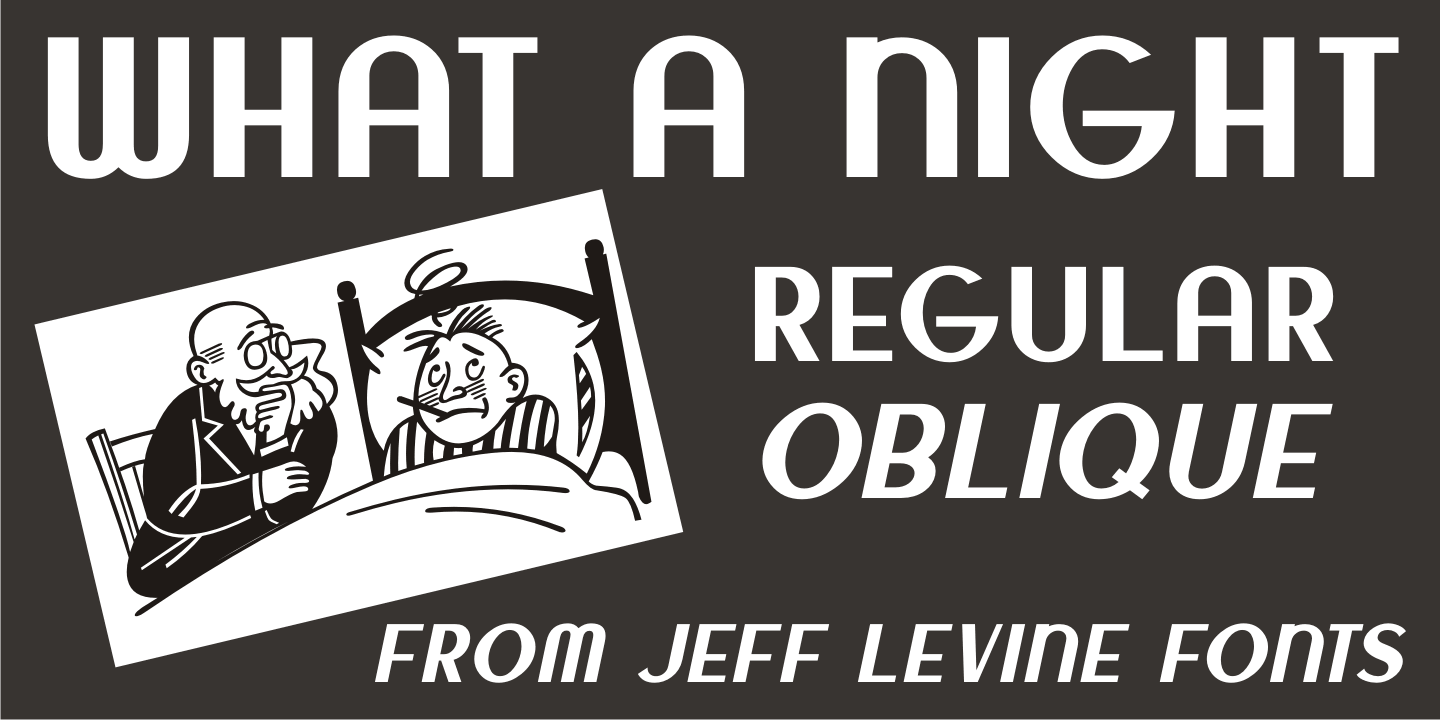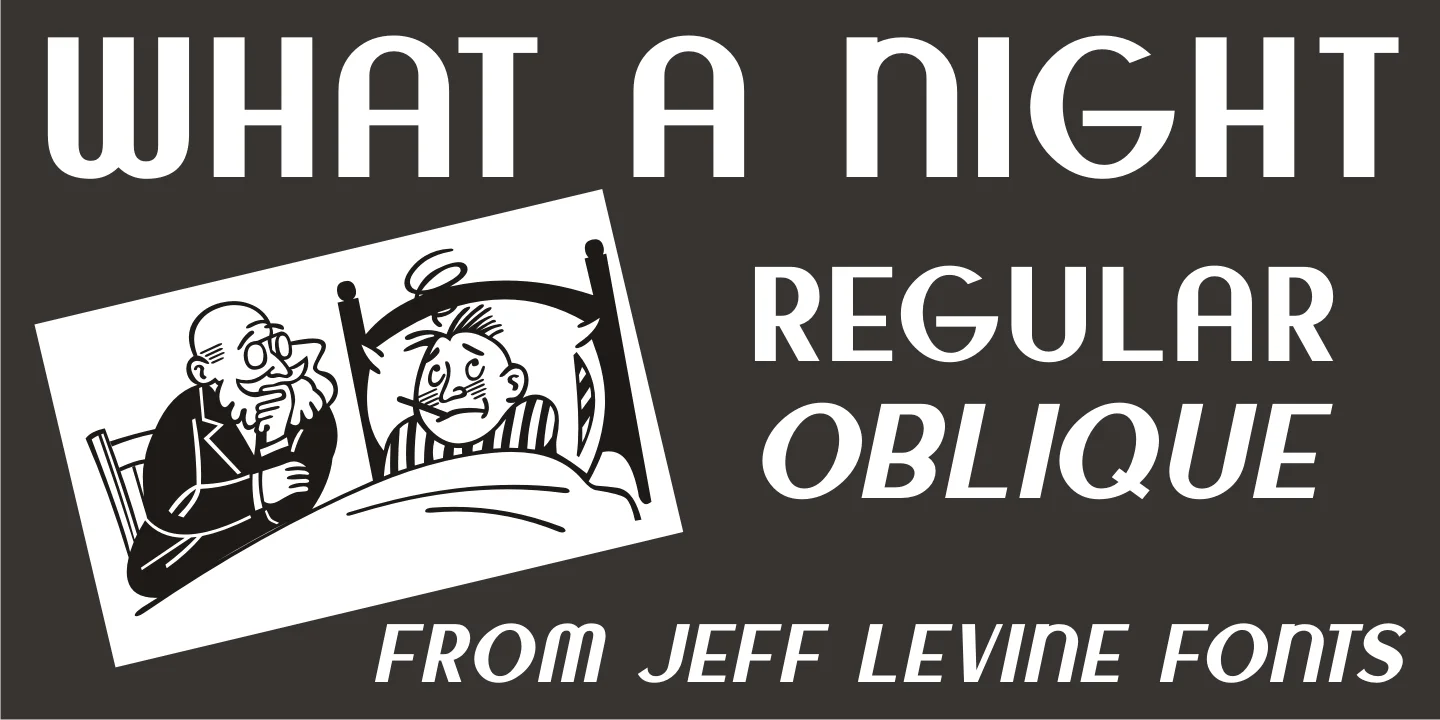
Надпись от руки на обложке нотной тетради "What A Night" 1934 года не только послужила образцом для дизайна What A Night JNL, но и стала его одноименным названием.
Цифровой шрифт доступен в обычной и наклонной версиях.